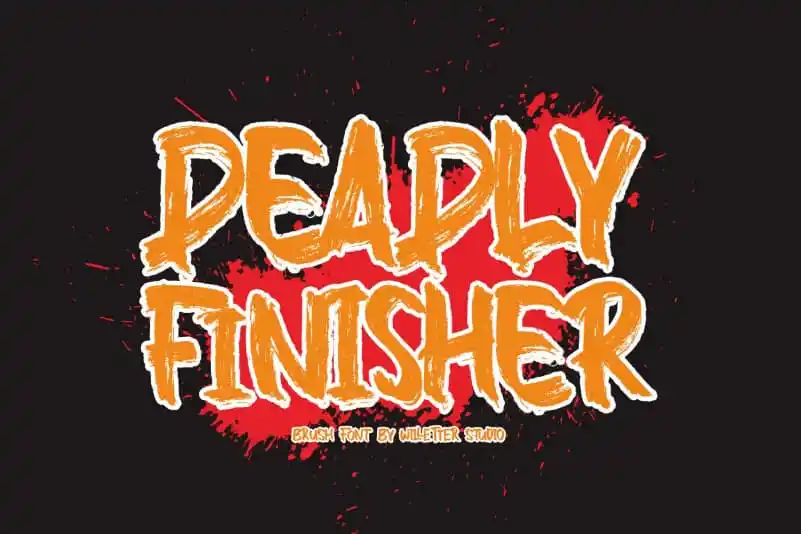
Deadly Finisher Brush Font – Download Grátis
A fonte ‘Deadly Finisher Brush Font’ é uma sensação moderna desenvolvida pela Will Std. Ela se destaca como uma tipografia brush que combina elementos casual e trendy, ideal para qualquer design informal. Com linhas fortes e preenchidas de cor negra, oferece suporte a letras em maiúsculas totalmente em todas as palavras (All Caps) e suporta múltiplos idiomas, tornando-a perfeita para títulos de filmes, títulos emocionantes, camisetas distoístas, conteúdos assustadores, publicações sociais, e design gráfico assustador. A fonte é uma escolha inteligente para quem busca um elemento único e criativo em seus projetos visuais.